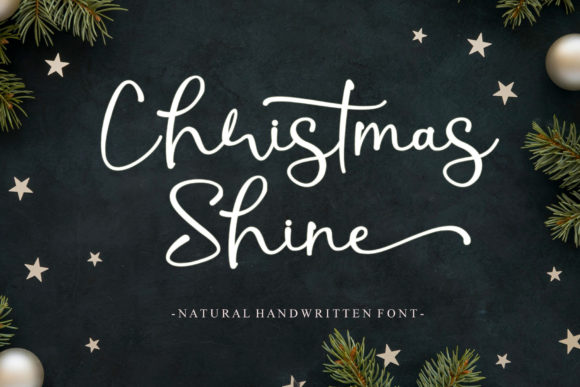
Christmas Shine
Mencari elemen reka bentuk yang sesuai boleh menjadi mencabar, tetapi Christmas Shine menawarkan koleksi luar biasa yang menaik taraf karya anda serta-merta.
Dicipta dengan ketepatan, Christmas Shine menyediakan vektor yang bersih, tipografi yang licin dan lesen komersial untuk ketenangan fikiran.
Sama ada anda mencipta produk POD (Print on Demand), jemputan perkahwinan atau grafik media sosial, Christmas Shine amat bersesuaian.